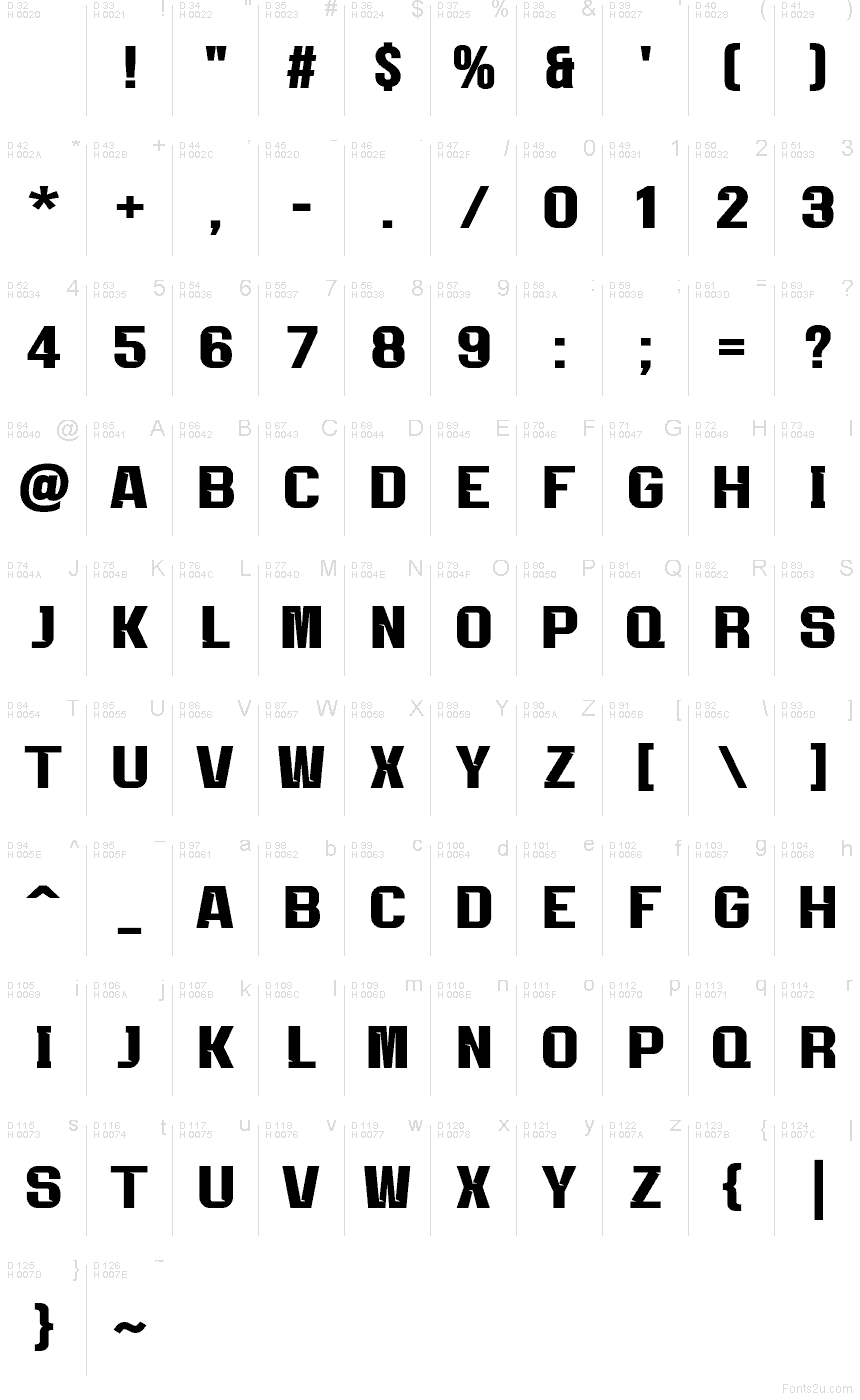
Games
Games od Graphicxell je bezplatné techno písmo typu display s tvrdým arkádovým charakterom a veľkými, blokovými verzálkami. Písmená pôsobia ako vytesané z masívnych čiernych platní, narušené ostrými šablónovými rezmi a klinovitými zárezmi, ktoré dodávajú abecede rýchly rytmus herných log.
Hodí sa na plagáty, e-športový branding, titulné obrazovky, grafiku pre streamerov, titulky a merch, kde krátke slová potrebujú úderný, súťaživý vzhľad. Ako bezplatné písmo funguje Games najlepšie v krátkych aplikáciách, ako sú titulné karty alebo monogramy, pretože hlboké rezy a robustné tvary pôsobia najenergickejšie, keď majú písmená dostatok priestoru.
Graphicxell